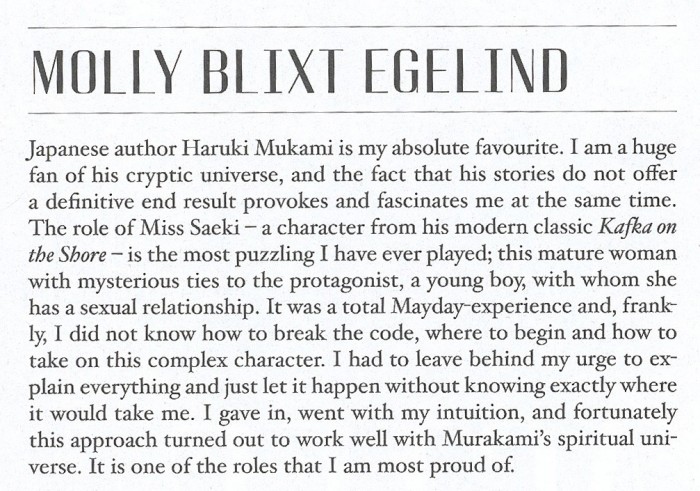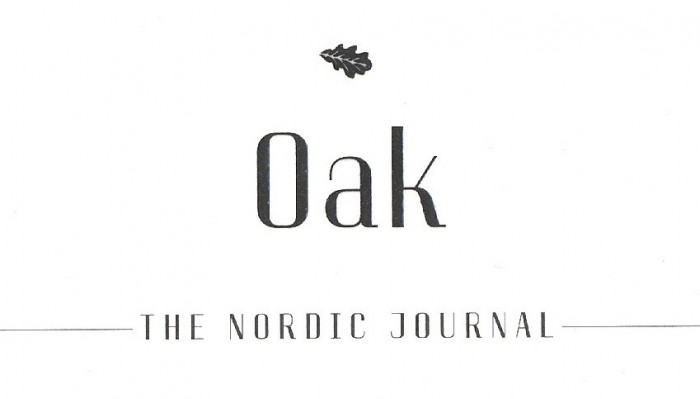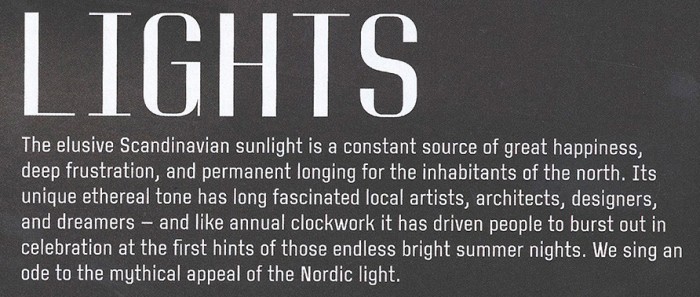
Welche Schriften ersatzweise verwenden? (Oak Journal)
für die Uni im Studiengang Kommunikationsdesign müssen wir ein Magazin nachgestalten (Es geht um Erfassung von Corporate Design etc.). Das mir zugeteilte Magazin ist die Oak (http://oakthenordicjournal.com).
Ich habe mit der Artidrection ein wenig hin und her geschrieben, um mehr über das CD zu erfahren. Das Problem, das sich mir jetzt stellt ist folgendes: Das Magazin verwendet eigens dafür entworfene Fonts (Oak Sans & Oak Serif), über die ich nicht verfüge.
Nun muss ich diese Schriften durch möglichst ähnliche ersetzen. Dies fällt mir insbesondere bei der klasstizistischen Antiqua schwer, da ich solche Schriften mit derartigen Strichstärkenkontrasten nur mit Serifen in meinem Fundus habe...
Habt ihr vielleicht ne Idee welche Fonts man gut als Ersatz nehmen könnte?
Für den Fließtext habe ich erstmal die Caslon gewählt, die passt schon ganz gut.
Es fehlen dann noch die Schrift für Headlines und Vorschalttexte (siehe Anhang).
Die Pecot passt ziemlich gut!